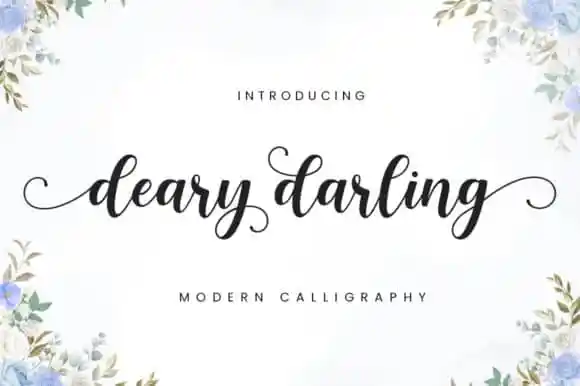
A fonte Deary Darling Calligraphy Font é uma moderna tipografia feita especialmente para os amantes do estilo script, oferecendo uma experiência única e única que vai lhe permitir criar designs atraentes e distintos. Se você está procurando por um recurso de tipografia que não apenas crie um visual elegante, mas também possua muitas características alternativas, então Deary Darling é o tipo de fonte para você. Com seu estilo moderno e charmoso, Deary Darling oferece uma solução perfeita para criar designs como convites de casamento, cartões de agradecimento, frases memoráveis, cartas de felicitações, logotipos, cartão de visita e qualquer outro tipo de design que possa se beneficiar de um toque pessoal. Este é o ideal para aqueles que buscam algo único em seu trabalho gráfico, combinando a sofisticação do estilo calligrafiado com a modernidade da tipografia moderna. Feita pela font designer Manjalistudio, Deary Darling oferece mais que simples estilos de escrita. Ela tem alternativas abundantes que permitem à criatividade florescer em seu projeto. Esta fonte é um verdadeiro acréscimo para qualquer design visual, especialmente aqueles que buscam uma pontada de personalidade e história em seus projetos. Seja você um designer profissional ou um amante do design, Deary Darling será definitivamente o tipo certo para adicionar um toque único e especial a seu próximo projeto.